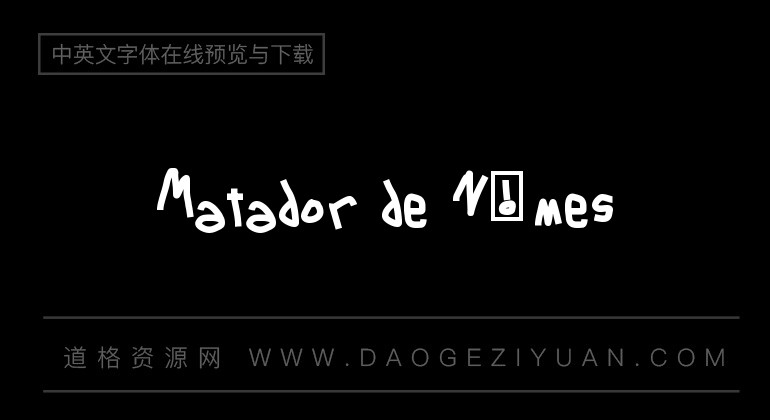
Matador de Nîmes 是一款由荷兰设计师 Jos Buivenga 创作的字体,它是一款特殊的手写字体,具有浓厚的古典风格。字体中的每一个字母都具有特殊的设计,使得它们看起来非常精致而又充满活力。Matador de Nîmes 字体具有良好的可读性,适用于各种类型的文本,并可以用于大多数的印刷和网页设计工作。内容介绍
Matador de Nîmes是一款非常不错的手写艺术字体,具有很好的视觉感,适合于文化类的宣传设计、商业类品牌的广告和产品包装设计以及个性化文字排版等较多场景。